싸인을 만들 때 많은 사람들이 공통적으로 실수하는 부분이 있어요. 이런 실수를 피하면 더 멋지고 실용적인 싸인을 만들 수 있답니다! ✍
내가 생각했을 때, 싸인은 단순한 서명이 아니라 나를 대표하는 중요한 요소예요. 특히 공식 문서나 계약서에서 사용할 일이 많다면 실용성과 가독성을 고려하는 것이 필수랍니다. ✅
이제 싸인 만들 때 가장 많이 하는 실수 5가지와 해결 방법을 알아볼까요? 🚀
1. 너무 복잡한 싸인 ❌
싸인이 멋있어 보이려고 너무 많은 선과 장식을 추가하는 경우가 많아요. 하지만 싸인은 실전에서 빠르고 자연스럽게 작성할 수 있어야 해요!
❌ 복잡한 싸인의 문제점 - 빠르게 쓰기 어렵고 시간이 오래 걸림 ⏳ - 한 번 쓸 때마다 다르게 보일 가능성이 큼 🔄 - 공식 문서에서 잘 알아보기 어려울 수 있음 📜
✅ 해결 방법 - 필요 없는 선과 장식을 줄이기 - 한두 개의 핵심적인 디자인 요소만 남기기 - 실제로 빠르게 싸인할 수 있도록 연습하기
📌 너무 복잡한 싸인의 단점 🔍
문제점 설명 작성 속도 저하 너무 많은 선과 곡선 때문에 빠르게 쓰기 어려움 일관성 부족 매번 다르게 보일 가능성이 커 신뢰도 저하 가독성 문제 공식 문서에서 알아보기 힘들고 흐릿해질 가능성 이제 알아보기 어려운 글씨체에 대한 실수를 살펴볼까요? 🔄
2. 알아보기 어려운 글씨체 🔄
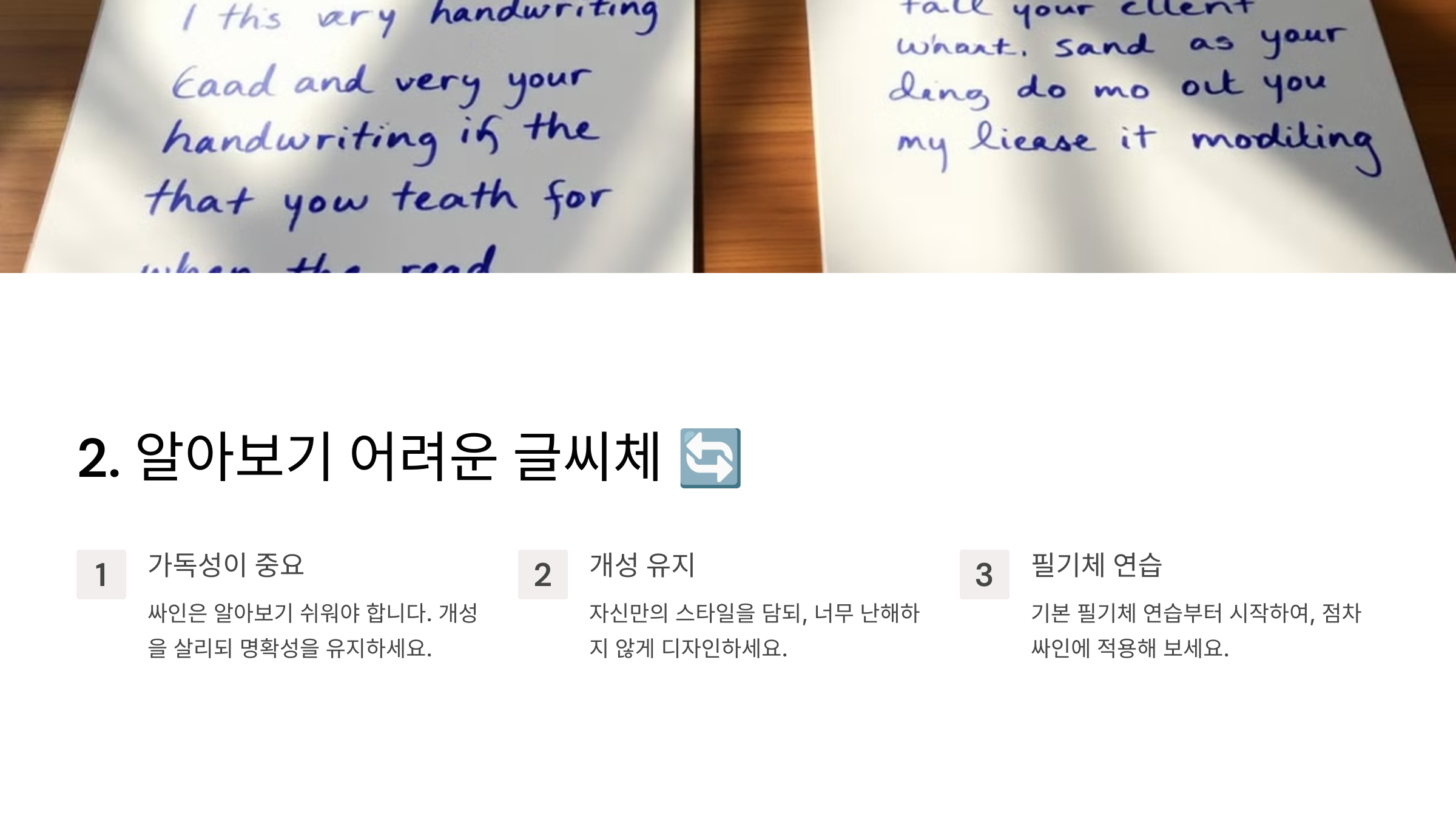
싸인은 개성이 중요하지만, 너무 복잡하거나 기울어진 글씨체는 오히려 가독성을 떨어뜨릴 수 있어요. 특히 공문서나 계약서에서는 명확하게 읽을 수 있는 싸인이 필수예요! 📜
❌ 어려운 글씨체의 문제점 - 글씨가 너무 기울어져 있거나 꼬여 있어서 읽기 어려움 - 시간이 지나면 본인조차 알아보기 어려울 수 있음 - 계약서나 공문서에서 문제가 될 가능성 있음 ⚠
✅ 해결 방법 - 필기체라도 너무 기울지 않게 디자인하기 - 글씨가 엉키지 않도록 간격 조절하기 - 한눈에 알아볼 수 있는 명확한 스타일 유지하기
📌 가독성이 떨어지는 싸인의 단점 📜
문제점 설명 읽기 어려움 글씨가 꼬이거나 겹쳐 있어 알아보기 힘듦 시간이 지나면 판독 불가 본인조차 나중에 읽기 어려울 수 있음 공식 문서 문제 계약서 등에서 법적 효력 문제 발생 가능 이제 싸인의 크기가 일정하지 않은 문제를 살펴볼까요? 📏
3. 싸인의 크기가 일정하지 않음 📏
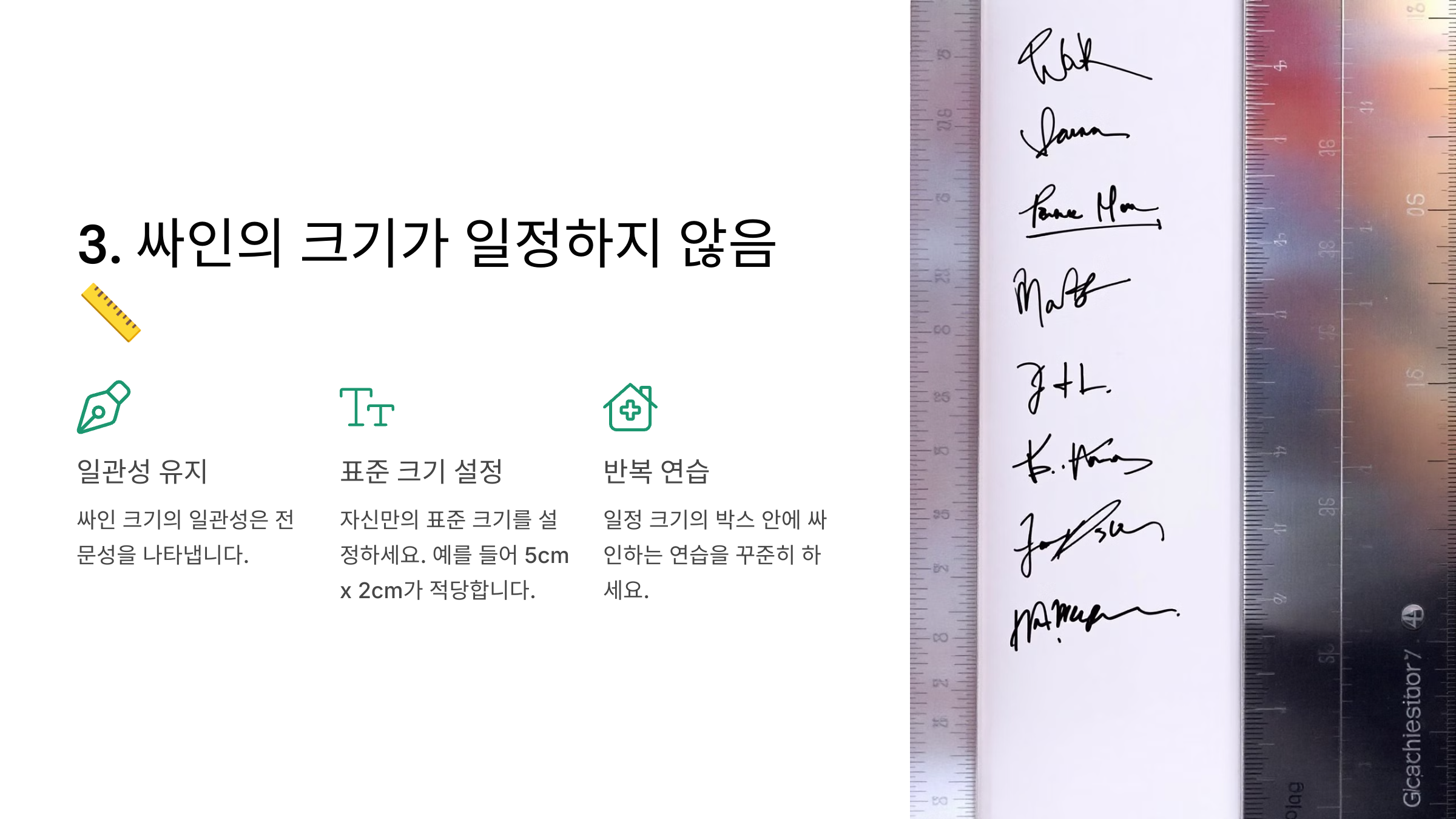
싸인은 항상 일정한 크기로 유지하는 것이 중요해요. 싸인을 할 때마다 크기가 달라지면 공식 문서나 계약서에서 신뢰도가 떨어질 수 있어요. 📜
❌ 일정하지 않은 싸인의 문제점 - 어떤 문서에서는 너무 크고, 어떤 문서에서는 너무 작음 - 싸인을 할 때마다 크기가 달라져 일관성이 부족 - 공문서나 금융 문서에서 신뢰도 저하 ⚠
✅ 해결 방법 - A4, 명함, 메모지 크기로 싸인을 연습하면서 적절한 크기 유지 - 싸인을 할 때 기준선을 정해 크기를 일정하게 유지 - 서류 크기에 맞게 조정하는 연습하기
📌 일정하지 않은 싸인의 단점 🎯
문제점 설명 일관성 부족 크기가 계속 달라져 신뢰도 저하 가독성 문제 너무 작으면 안 보이고, 너무 크면 공간 차지 공식 문서에서 문제 발생 계약서, 금융 서류에서 신뢰성 부족 이제 속도감 없이 너무 느리게 싸인하는 문제를 살펴볼까요? ⏳
4. 속도감 없이 너무 느리게 싸인 ⏳
싸인은 빠르고 자연스럽게 작성할 수 있어야 해요. 너무 천천히 쓰면 일관성이 깨지고, 실전에서 불편할 수 있어요. 🖊
❌ 느린 싸인의 문제점 - 공문서나 계약서 작성 시 시간이 오래 걸림 - 서명을 할 때마다 싸인의 모양이 달라질 가능성이 높음 - 속도가 느려지면서 손의 흐름이 부자연스러워질 수 있음 ⚠
✅ 해결 방법 - 빠른 속도로도 유지할 수 있는 싸인 디자인 연습하기 - 너무 정교한 선보다는 간결한 스타일로 수정 - 5초 이내에 싸인을 끝낼 수 있도록 연습하기
📌 싸인을 너무 느리게 할 때의 단점 ⏳
문제점 설명 서명 속도 저하 공식 문서 작성 시 시간이 오래 걸림 일관성 부족 매번 다른 모양으로 싸인될 가능성이 높음 손의 흐름이 부자연스러움 너무 신경 쓰다 보면 필기 흐름이 어색해짐 이제 싸인을 할 때마다 다르게 하는 문제를 살펴볼까요? ⚠
5. 싸인을 매번 다르게 함 ⚠
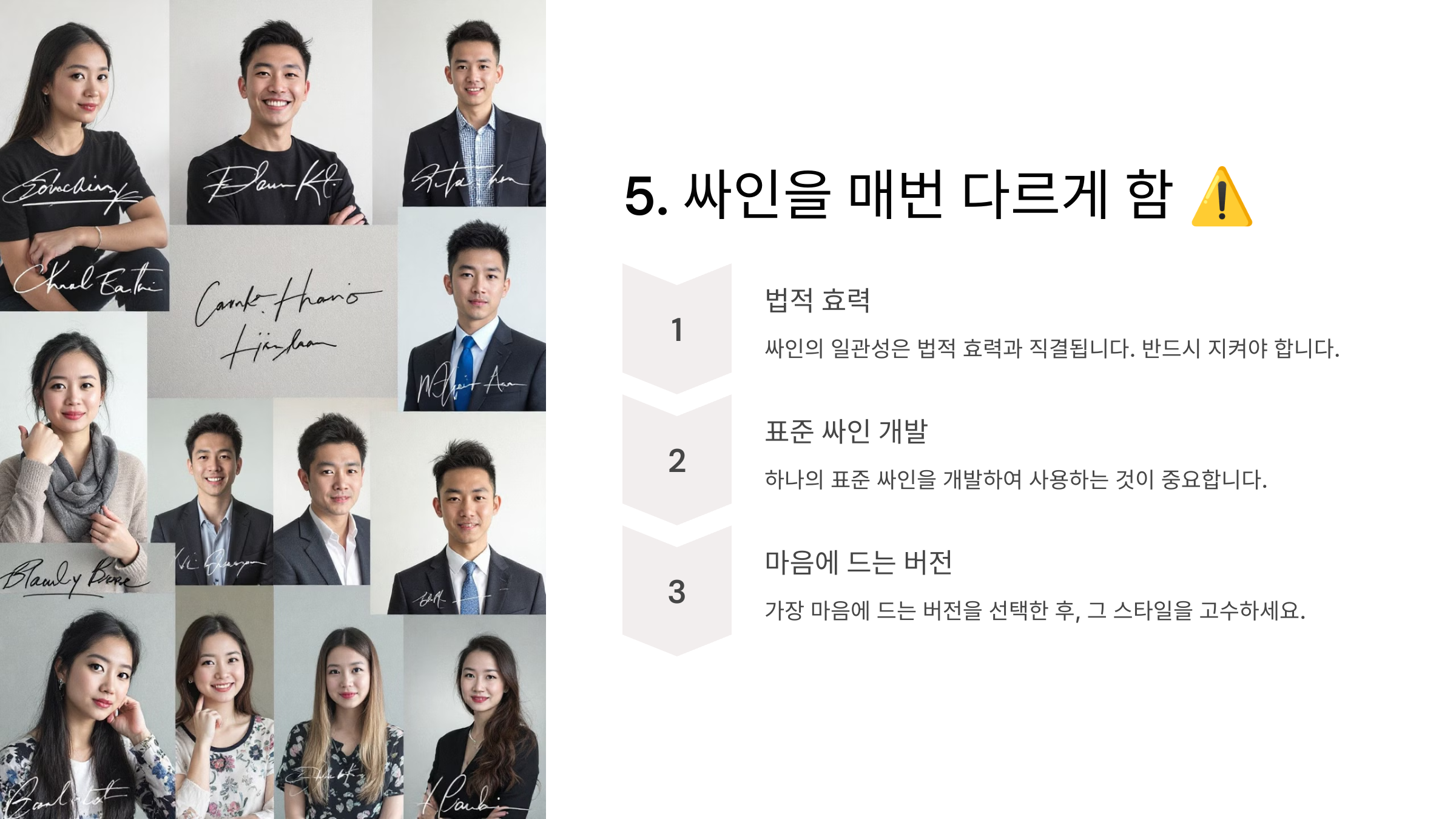
싸인은 일관성이 가장 중요한 요소 중 하나예요. 매번 다르게 싸인을 하면 본인 확인이 어려워질 수 있고, 공식 문서에서 문제가 될 수도 있어요. 🖊
❌ 일관성 없는 싸인의 문제점 - 서명할 때마다 다른 모양이 되어 신뢰도가 낮아짐 - 공식 문서, 은행 서류에서 본인 확인이 어려울 수 있음 - 오랜 시간이 지나면 본인도 싸인을 헷갈릴 가능성 ⚠
✅ 해결 방법 - 한 가지 스타일을 정하고 지속적으로 연습 - 눈 감고 싸인해도 같은 모양이 나올 때까지 연습하기 - 디지털 싸인을 만들어 동일한 스타일 유지하기
📌 싸인의 일관성이 부족할 때 문제점 📜
문제점 설명 신뢰도 저하 매번 다른 모양이 되어 일관성 부족 본인 확인 문제 공문서, 금융 서류에서 동일인 확인이 어려움 기억하기 어려움 오랜 시간이 지나면 본인도 싸인을 헷갈릴 가능성 이제 올바른 싸인 만들기 위한 팁을 알아볼까요? 🎯
올바른 싸인 만들기 위한 팁 🎯
싸인을 만들 때 실용성과 개성을 동시에 살리는 것이 중요해요. 아래 팁을 참고하면 빠르고 멋지면서도 신뢰감을 주는 싸인을 완성할 수 있어요! ✍
✅ 한 가지 스타일을 정해 반복 연습 - 너무 자주 바꾸지 말고 한 가지 스타일을 유지하는 것이 중요해요.
✅ 간결하면서도 개성을 살리기 - 필기체, 이니셜, 기호(⭐, ❤) 등을 적절히 활용하여 차별화하세요.
✅ 눈 감고 싸인 연습하기 - 손이 기억할 수 있도록 반복 연습해서 일관성을 유지하세요.
✅ 다양한 크기로 연습하기 - A4, 명함, 포스트잇 등 다양한 크기의 종이에 싸인을 해보세요.
📌 올바른 싸인 만들기 핵심 요소 ✨
팁 설명 일관성 유지 싸인을 매번 같은 스타일로 유지하기 간결한 디자인 너무 복잡하지 않도록 심플하게 구성 자연스러운 흐름 필기체 스타일을 활용하여 부드럽게 연결 빠른 속도 5초 이내에 싸인할 수 있도록 연습 크기 조절 공식 문서, 명함 등 다양한 크기에서 테스트 이제 싸인에 대한 궁금증을 해결할 시간! FAQ에서 자주 묻는 질문을 정리해 볼까요? ❓
FAQ ❓
Q1. 싸인을 만들 때 가장 중요한 요소는 무엇인가요?
A1. 싸인은 일관성, 속도, 가독성, 개성이 중요해요. 너무 복잡하면 빠르게 쓰기 어렵고, 너무 단순하면 개성이 부족할 수 있어요. 간결하면서도 나만의 스타일을 반영하는 것이 좋아요. ✍
Q2. 싸인의 크기는 어느 정도가 적당한가요?
A2. 싸인은 너무 크면 문서에서 공간을 많이 차지하고, 너무 작으면 가독성이 떨어질 수 있어요. A4 용지, 명함, 포스트잇 등 다양한 크기로 테스트하면서 적절한 크기를 찾는 것이 좋아요. 📏
Q3. 싸인을 바꾸면 법적 문제가 생길 수도 있나요?
A3. 법적으로 인정되는 문서에서는 기존 싸인과 다르면 문제가 될 수도 있어요. 따라서 한 가지 싸인을 정해 꾸준히 사용하는 것이 중요해요. 만약 싸인을 변경할 경우, 은행이나 공공기관에 미리 등록된 싸인을 업데이트해야 해요. ✅
Q4. 싸인에 기호(하트, 별 등)를 넣어도 괜찮을까요?
A4. 네! 기호를 넣으면 개성이 강조되고, 더욱 기억에 남는 싸인이 될 수 있어요. 하지만 너무 많은 기호를 넣으면 복잡해 보일 수 있으니 적절히 활용하는 것이 좋아요. ⭐❤⚡
Q5. 싸인 연습을 효과적으로 하는 방법이 있을까요?
A5. 반복적인 연습이 필수예요! 먼저 원하는 스타일을 정한 후, 1) 눈 감고 써보기 2) 다양한 크기로 연습하기 3) 빠른 속도로 써보기 이런 방식으로 연습하면 자연스럽고 멋진 싸인을 만들 수 있어요. 🚀
Q6. 싸인을 디지털 파일로 저장하는 방법은?
A6. 태블릿이나 스마트폰에서 스타일러스 펜을 이용해 싸인을 작성한 후 PNG 파일로 저장하면 활용할 수 있어요. Adobe Sign, DocuSign 같은 전자 서명 도구도 유용해요. 💻
Q7. 한글 싸인과 영어 싸인 중 어떤 것이 더 좋을까요?
A7. 사용 목적에 따라 달라요. - 한글 싸인: 독창적인 느낌을 줄 수 있어요. - 영어 싸인: 글로벌한 이미지와 간결한 디자인을 만들기 좋아요. 본인의 필요에 따라 선택하는 것이 가장 좋아요! ✅
Q8. 싸인을 바꾸면 운이 바뀐다는 말이 있던데, 사실인가요?
A8. 과학적인 근거는 없지만, 싸인을 바꾸면 자신감과 이미지가 달라지는 효과가 있어요. 특히, 성공한 사람들의 싸인을 보면 개성이 뚜렷한 경우가 많아요. 💯
이제 싸인 만들 때 실수하지 않고, 완벽한 나만의 싸인을 완성할 수 있겠죠? 🚀 꾸준히 연습해서 멋진 싸인을 만들어보세요! ✨